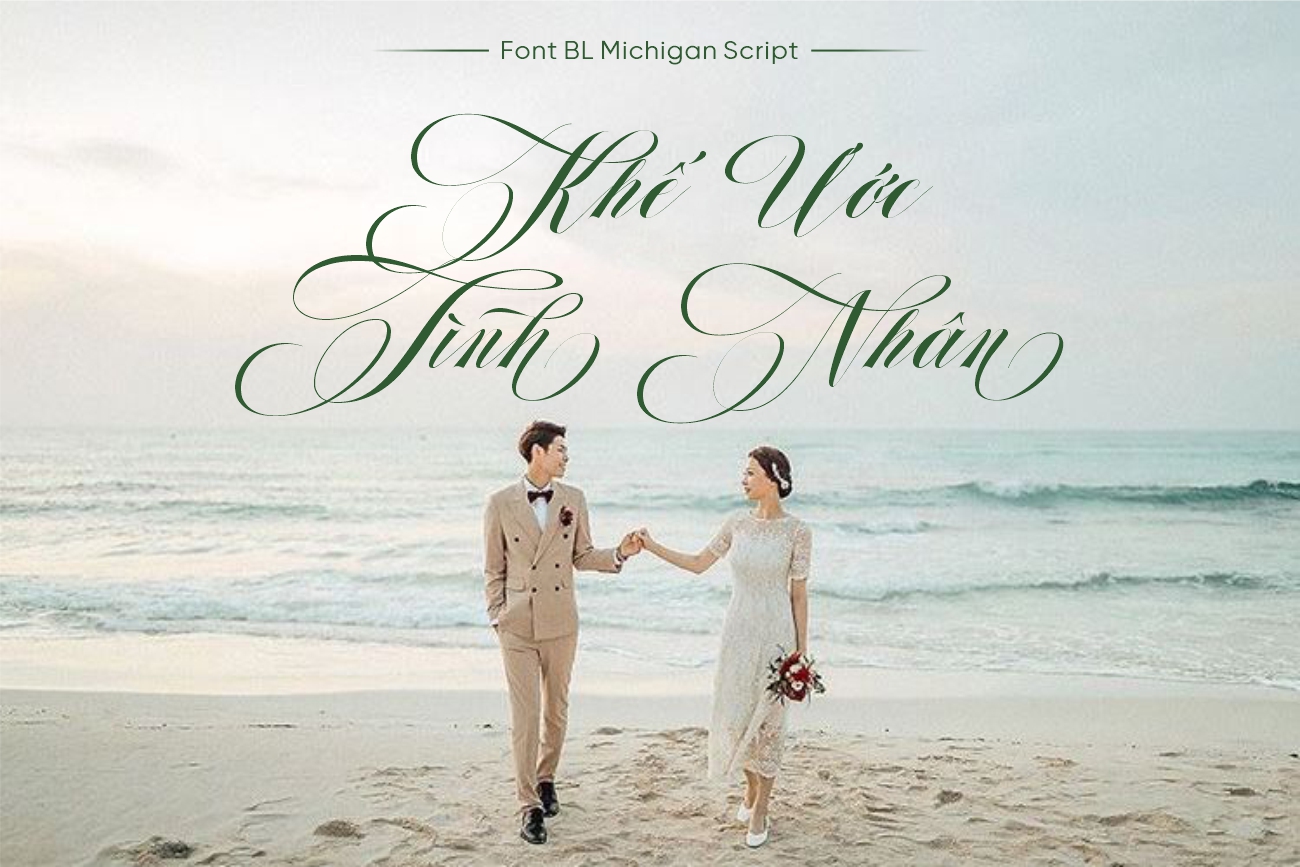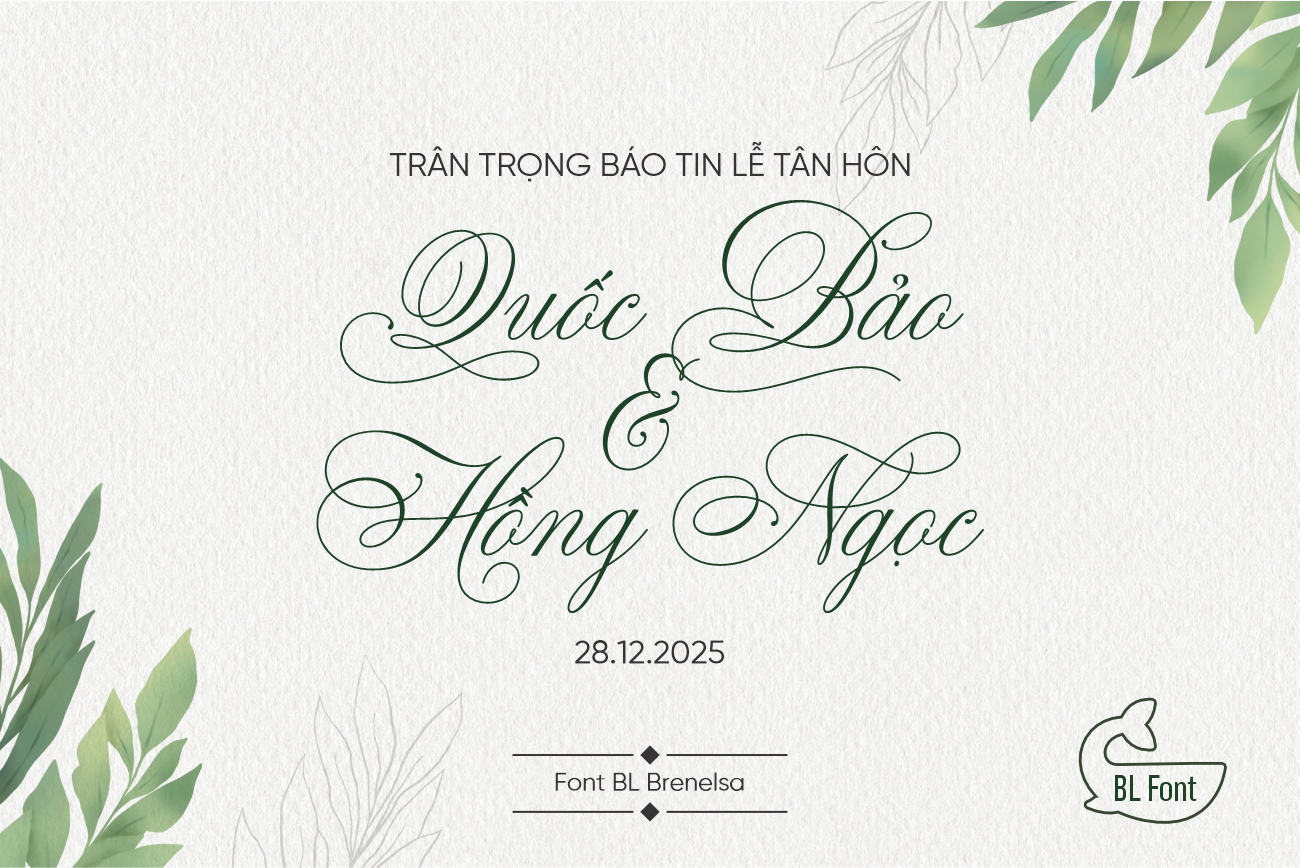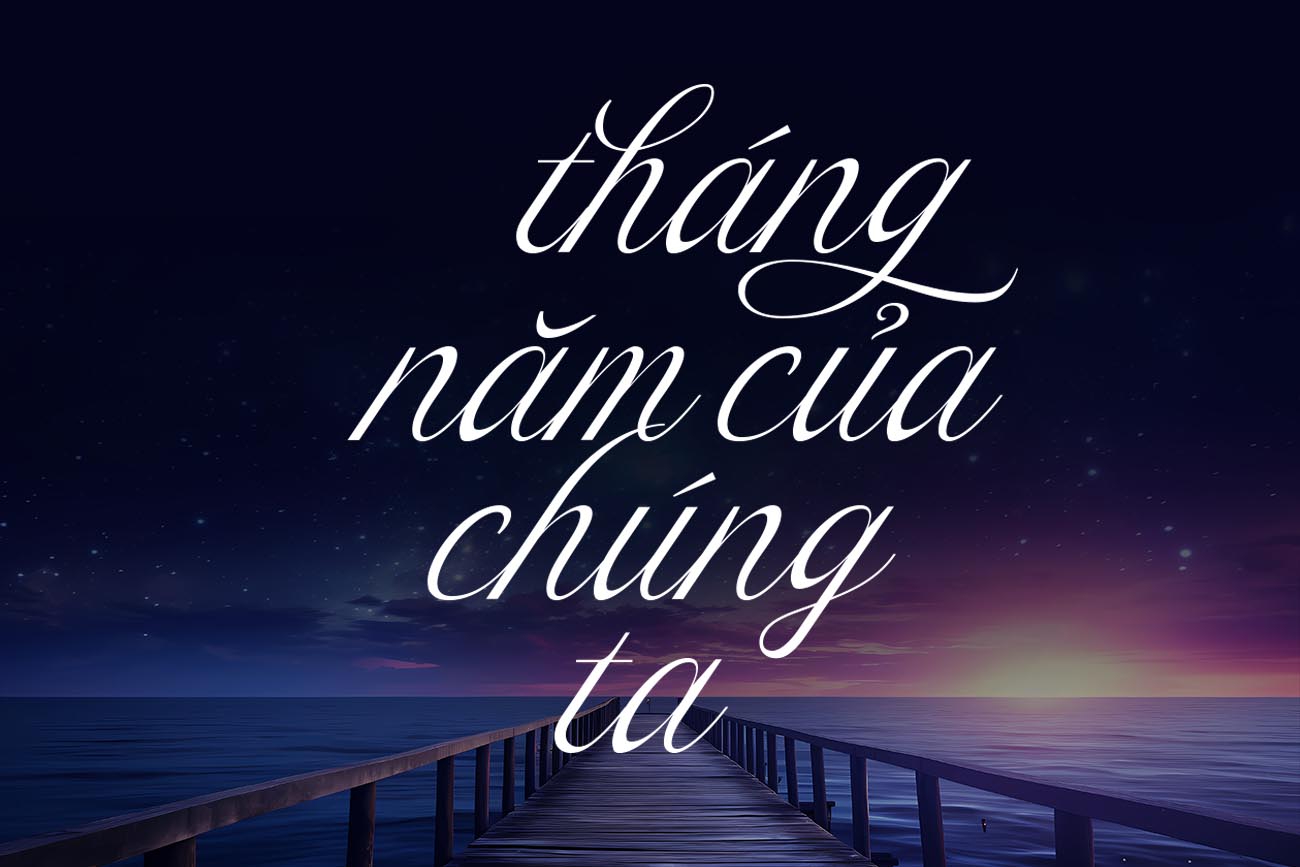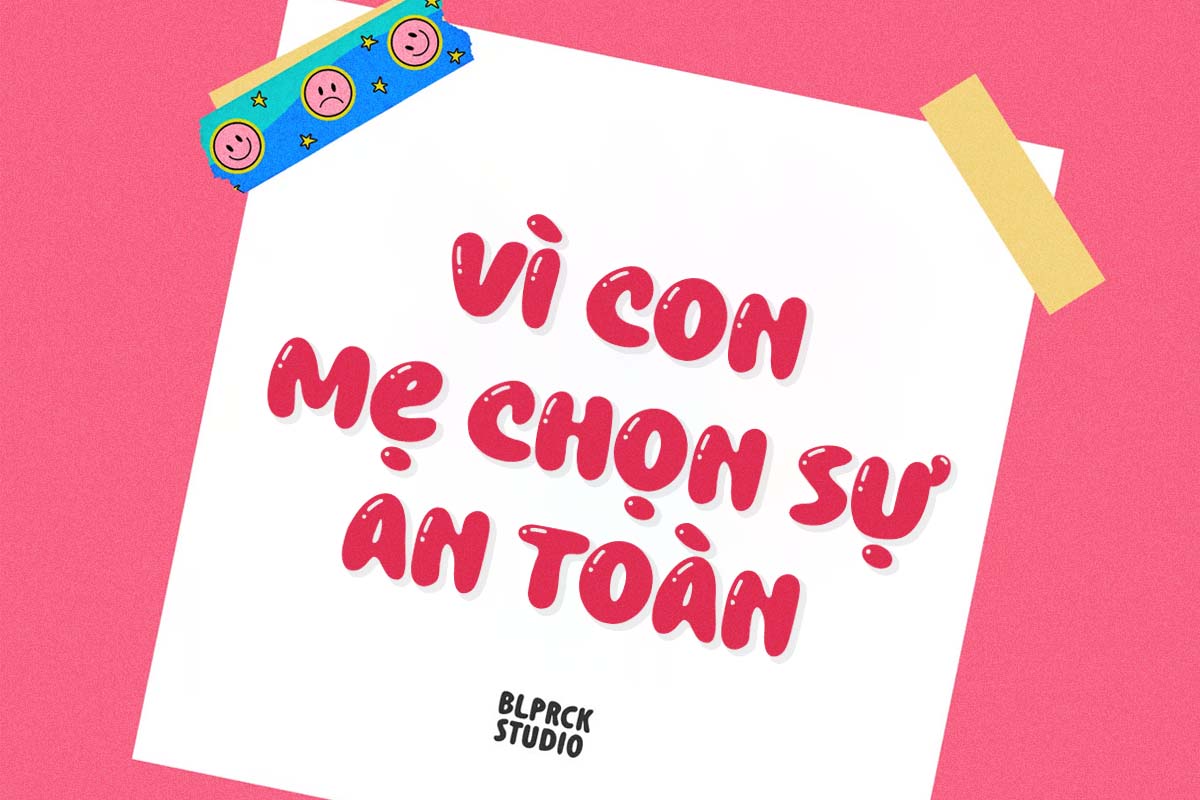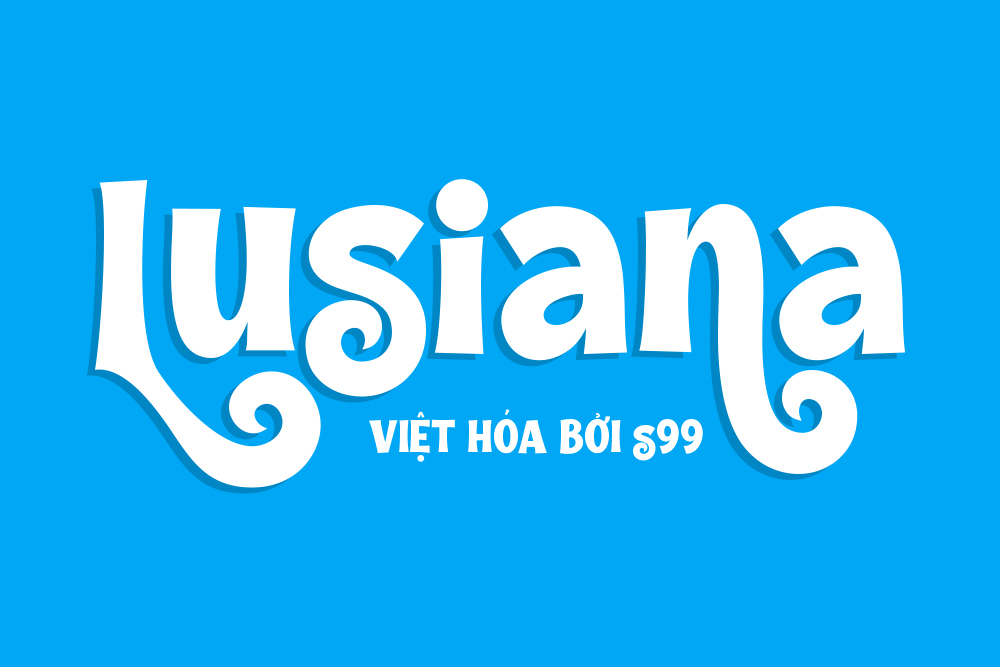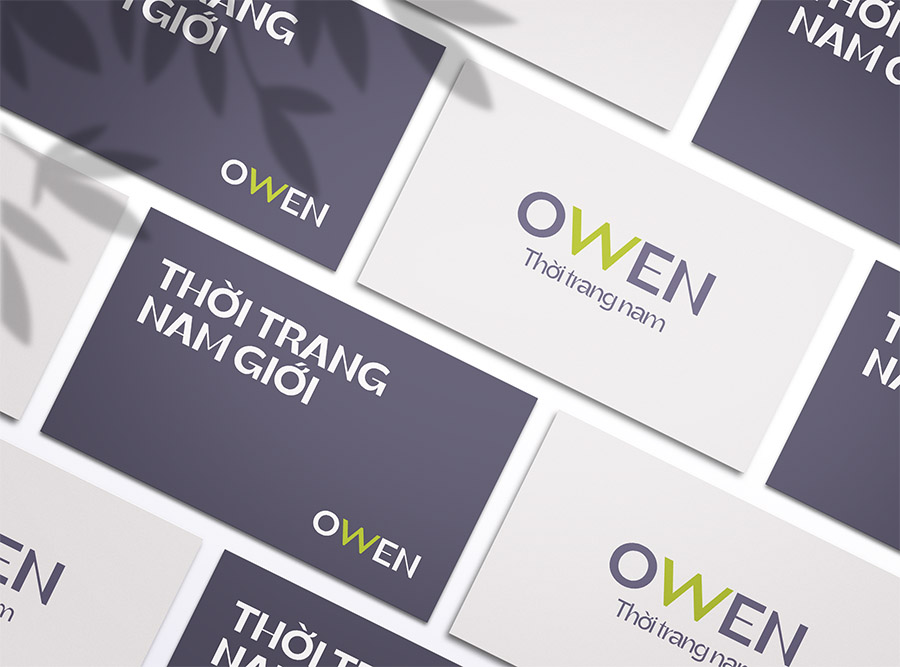
Tổng Hợp 18 Font Chữ Logo Việt Hóa Có Dấu
Font chữ logo là yếu tố quan trọng giúp thương hiệu tạo dấu ấn ngay từ ánh nhìn đầu tiên. Một bộ font đẹp, Việt hóa đầy đủ không chỉ giúp logo dễ đọc, chuyên nghiệp mà còn truyền tải cảm xúc và cá tính riêng của thương hiệu. Từ phong cách hiện đại, tối giản, đến serif sang trọng hay script nghệ thuật, mỗi loại font đều có vai trò riêng trong việc nâng tầm nhận diện thương hiệu.
Font Chữ Logo Việt hóa là gì?
Định nghĩa
Font chữ Logo Việt hóa là những bộ phông chữ được tuyển chọn và tối ưu dấu tiếng Việt hoàn chỉnh, chuyên dùng cho thiết kế nhận diện thương hiệu. Sử dụng các font này giúp Designer tự do sáng tạo logo chuyên nghiệp, ấn tượng và truyền tải trọn vẹn thông điệp mà không lo gặp lỗi hiển thị ký tự.
Đặc điểm nổi bật
- Đường nét rõ ràng, dễ nhận diện
- Tạo cá tính và phong cách riêng cho thương hiệu
- Phù hợp với nhiều định dạng: in ấn, website, app, banner
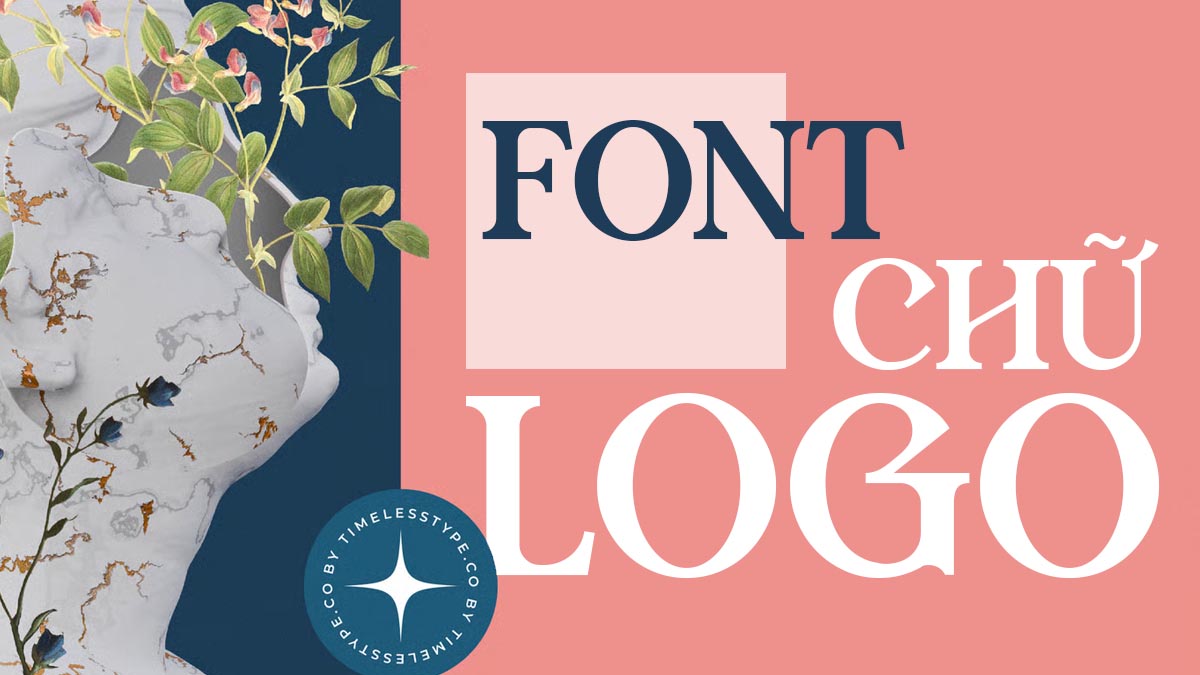
Ứng Dụng Của Font Chữ Logo Trong Thiết Kế
Trong thiết kế hiện đại, font chữ logo không chỉ để “làm đẹp” – mà còn giúp thương hiệu ghi dấu ấn mạnh mẽ và truyền tải thông điệp rõ ràng.
Dưới đây là cách các designer thường sử dụng:
- Logo thương hiệu & bao bì sản phẩm: Gợi cảm giác hiện đại, sang trọng hoặc vui nhộn tùy phong cách.
- Poster, banner & quảng cáo: Tạo tiêu đề nổi bật, dễ nhận diện.
- Website & giao diện thương mại điện tử: Giúp nhận diện thương hiệu, tăng tính thẩm mỹ.
- Thiệp mời, brochure, ấn phẩm truyền thông: Mang cá tính, sự chuyên nghiệp hoặc thân thiện.
- Video quảng bá & TVC: Dùng cho tagline, tiêu đề nhấn mạnh thương hiệu.
Danh sách Font Chữ Logo Việt Hóa Cho Mọi Ngành Nghề
Dưới đây là bộ sưu tập những font chữ logo Việt hóa hiện đại, đa dạng, dễ dùng, được tuyển chọn kỹ lưỡng bởi đội ngũ Fontdep.vn:
1. Font Chữ Logo TH Hoaico 20 Hiện Đại & Tối Giản Việt Hoá
TH Hoaico 20 sở hữu nét chữ tối giản, cân đối, mang tinh thần hiện đại và trẻ trung. Đường nét gọn gàng, giúp logo nổi bật nhưng vẫn giữ sự thanh lịch. Font rất linh hoạt khi áp dụng cho tiêu đề, tagline hay nhận diện thương hiệu. Khả năng Việt hóa đầy đủ giúp trình bày tiếng Việt chuẩn mực mà vẫn giữ thẩm mỹ. Đây là lựa chọn lý tưởng cho các thương hiệu start-up hoặc công ty hiện đại.
2. Font Chữ Logo Cobe Sans Serif Hiện Đại & Linh Hoạt Việt Hoá
Cobe Sans Serif là font sans serif với các đường nét sạch, cân đối, mang cảm giác năng động, hiện đại và tối giản. Font vừa linh hoạt vừa dễ đọc, giúp thiết kế nổi bật sự gọn gàng, trẻ trung và chuyên nghiệp. Lý tưởng cho logo, website, ấn phẩm marketing số, poster hoặc bất kỳ thiết kế nào cần phong cách hiện đại, linh hoạt và dễ nhận diện.
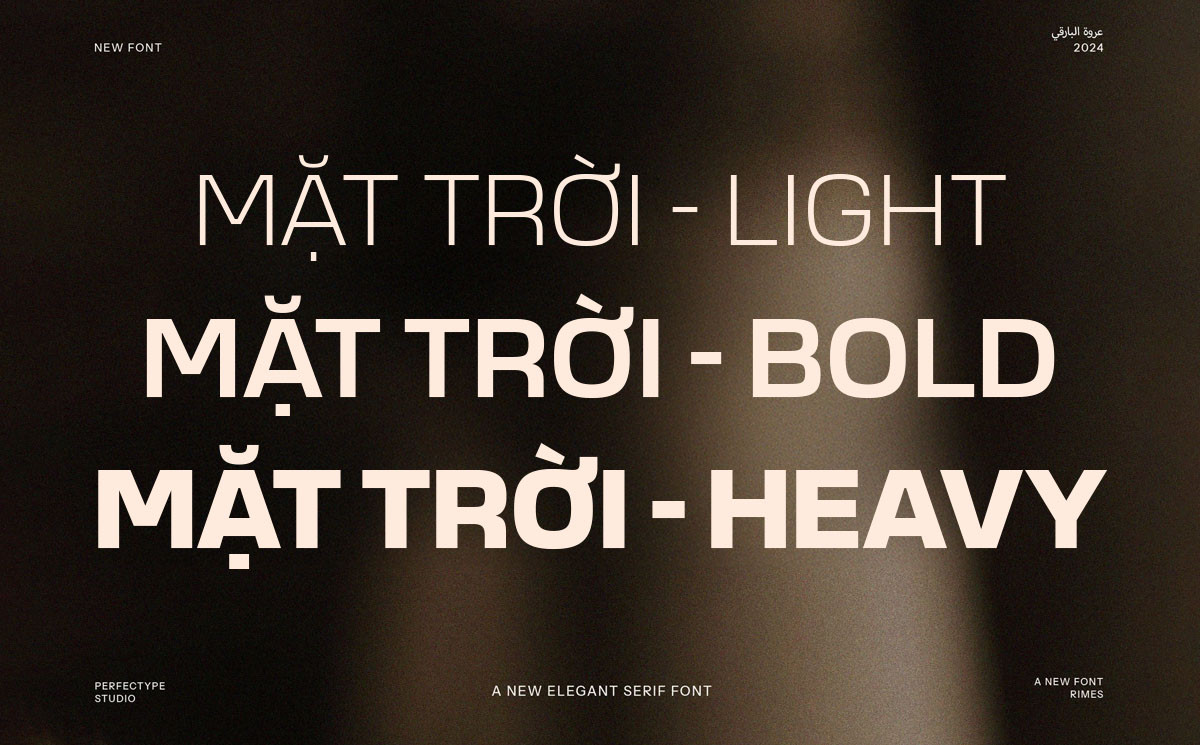
3. Font Chữ Logo Blayzer Slab Serif Cứng Cáp & Ấn Tượng Việt Hoá
Blayzer Slab là font slab serif với các đường nét mạnh mẽ, độ tương phản dày–mỏng rõ ràng, tạo cảm giác chắc chắn, quyền lực và đáng tin cậy. Font mang phong cách hiện đại nhưng đầy ấn tượng, giúp thiết kế nổi bật và ghi nhớ ngay từ cái nhìn đầu tiên. Hoàn hảo cho logo thương hiệu cần tạo ấn tượng mạnh, các lĩnh vực công nghiệp, kiến trúc, poster hoặc bao bì sản phẩm đòi hỏi sự cứng cáp và chuyên nghiệp.
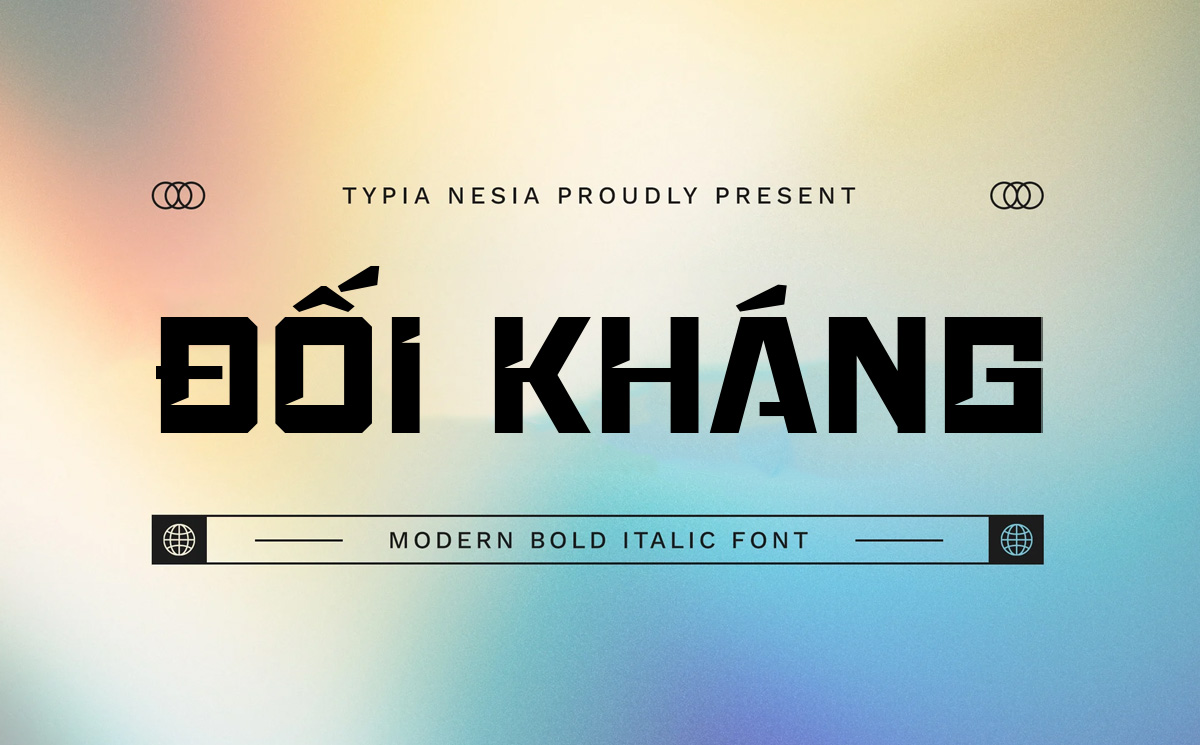
4. Font Chữ Logo TH Manisans Hiện Đại & Sang Trọng Việt Hoá
TH Manisans là font logo với các đường nét tinh tế, thanh thoát, kết hợp giữa phong cách hiện đại và sang trọng. Font giúp thiết kế nổi bật sự chuyên nghiệp, thanh lịch, phù hợp với nhiều loại ấn phẩm cao cấp. Lý tưởng cho logo, branding cao cấp, poster, bao bì sản phẩm hoặc các ấn phẩm quảng cáo cần phong cách hiện đại, sang trọng và tinh tế.
- Tác giả gốc: Måns Grebäck
- Việt hóa bởi: Font TH
5. Font Chữ Logo TH Luxury 6 Sang Trọng & Tinh Tế Việt Hoá
TH Luxury 6 là font serif với các đường nét thanh lịch, tinh tế, mang đến cảm giác cao cấp và chuyên nghiệp. Font giúp thiết kế nổi bật sự sang trọng mà vẫn giữ được sự mềm mại, dễ đọc và tinh tế. Hoàn hảo cho logo spa, thương hiệu thời trang, mỹ phẩm, bao bì sản phẩm hoặc bất kỳ thiết kế nào cần phong cách sang trọng, tinh tế và chuyên nghiệp.
- Tác giả gốc: Đang update
- Việt hóa bởi: Phạm Sơn
6. Font Chữ Logo TH Runalto Hiện Đại & Đẳng Cấp Việt Hoá
TH Runalto là font serif với các đường nét mạnh mẽ, tinh tế và rõ ràng, mang đến cảm giác hiện đại, sang trọng và dễ đọc. Font giúp thiết kế nổi bật, vừa chuyên nghiệp vừa đẳng cấp, phù hợp với các thương hiệu cao cấp. Lý tưởng cho logo cao cấp, tiêu đề thương hiệu, poster, bao bì sản phẩm hoặc bất kỳ thiết kế nào cần phong cách hiện đại, tinh tế và đẳng cấp.
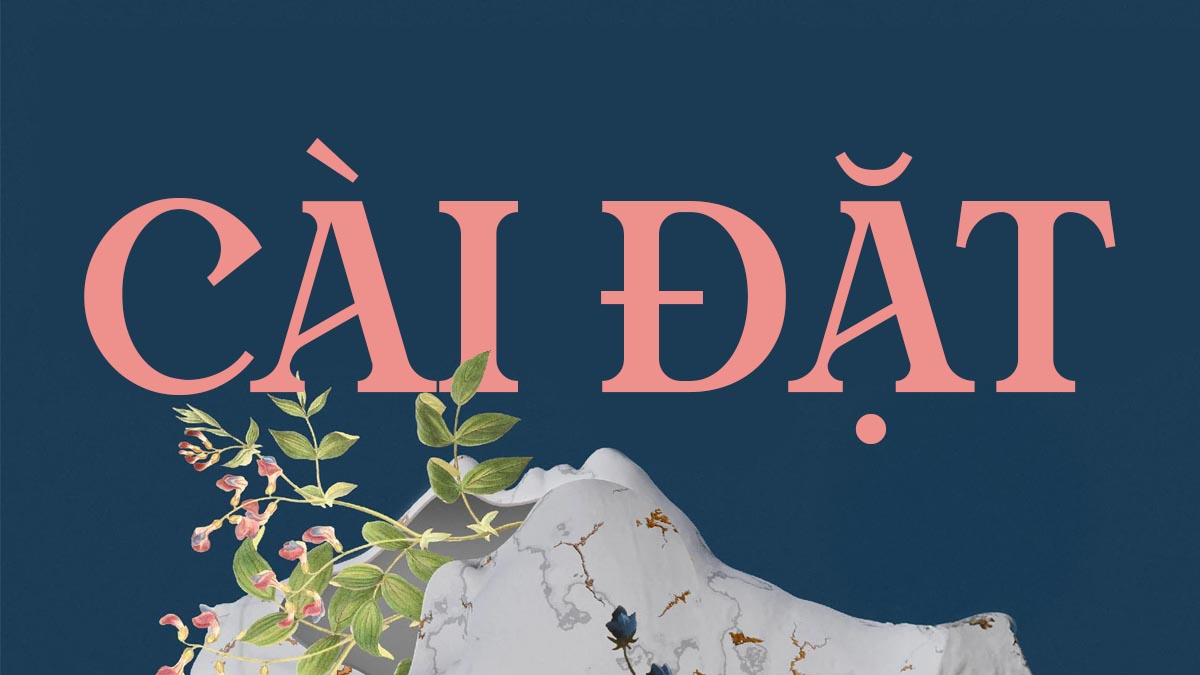
Kết Luận
Bộ sưu tập font logo Việt hóa này giúp bạn chọn lựa phong cách phù hợp: từ hiện đại, tối giản, sang trọng, nghệ thuật đến vui nhộn. Chọn đúng font sẽ nâng tầm nhận diện thương hiệu, tạo logo chuyên nghiệp và dễ nhớ, giúp thương hiệu nổi bật trong mọi thiết kế.